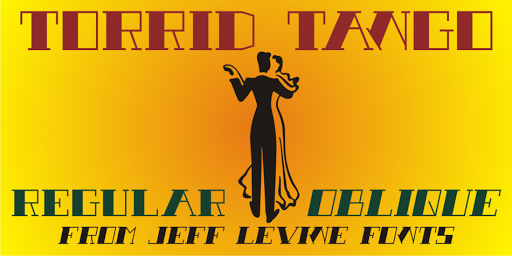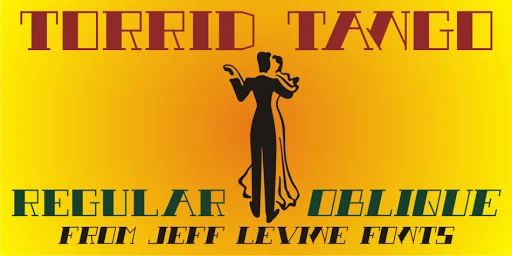
Название: Torrid Tango Font (2021)
На нотах "Tangos Pour Manon" 1920-х годов из Брюсселя, Бельгия, заголовок был написан от руки в необычном стиле.
Алфавит был квадратным, с засечками и толстыми и тонкими штрихами, которые были более популярны в наступающем ар-деко 1930-х и 1940-х годов.
Это стало рабочей моделью для Torrid Tango JNL, который доступен в обычной и наклонной версиях